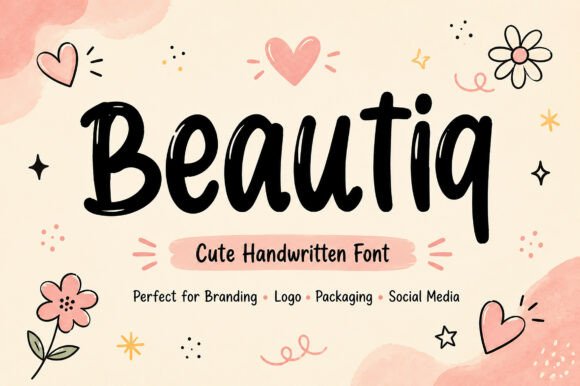
Beautiq
Beautiqのような高品質の素材をお探しの場合、このプレミアムパッケージはクリエイティブなプロジェクトに素晴らしい選択です。
精密に作られたBeautiqは、クリーンなベクター、滑らかなタイポグラフィ、そして安心のための商用ライセンスを提供します。
POD(オンデマンド印刷)製品、結婚式の招待状、またはソーシャルメディアのグラフィックを作成している場合でも、Beautiqは理想的です。